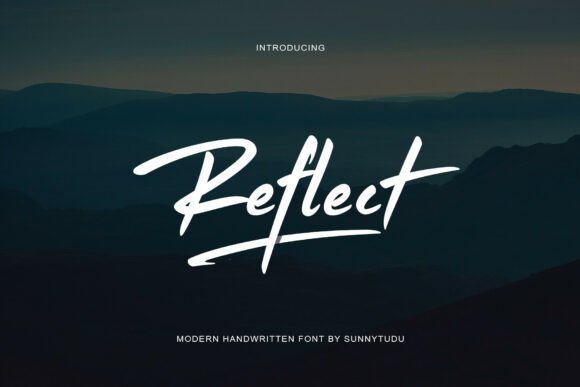
Reflect Handwritten Font
適切なデザイン要素を見つけるのは難しい場合がありますが、Reflect Handwritten Fontは作品を即座に引き立てる優れたコレクションを提供します。
POD(オンデマンド印刷)製品、結婚式の招待状、またはソーシャルメディアのグラフィックを作成している場合でも、Reflect Handwritten Fontは理想的です。